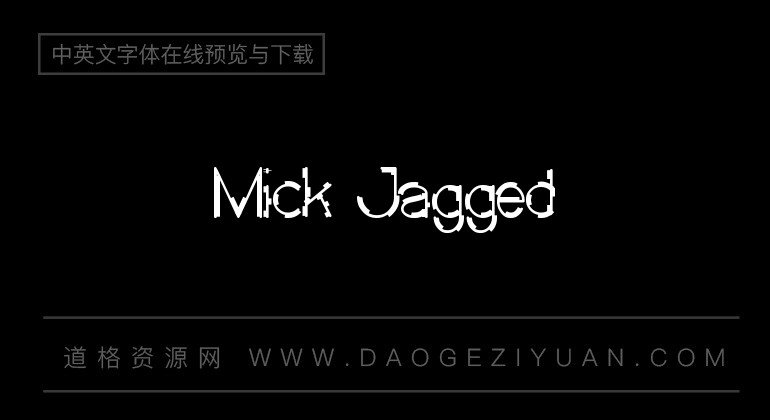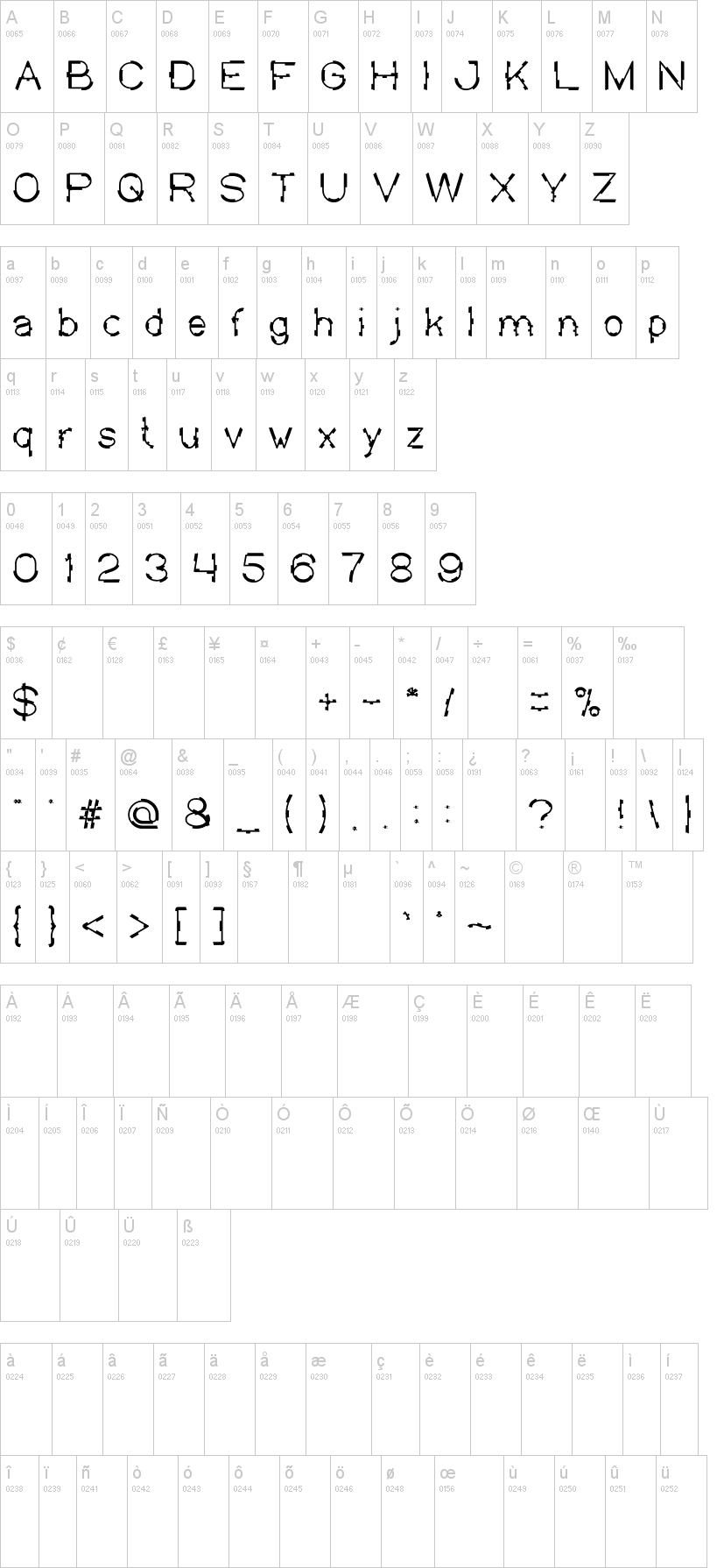
我想您可能指的是 Mick Jagger 字体,而不是 Mick Jagged 字体。 Mick Jagger 字体是一种手写风格的字体,以滚石乐队的主唱 Mick Jagger 命名,因为它的设计灵感来自于他的手写风格。 这种字体具有一种独特的,有点粗糙的感觉,看起来像是手写在纸上的字体,但实际上是计算机生成的。它的艺术风格适用于标题、标志和海报等设计项目。 Mick Jagger 字体由设计师 Ronnie Tjampitjinpa 和 Georgia Chapman 创造,可以从许多免费字体下载网站获得。内容介绍
Mick Jagged是一款非常不错的手写艺术字体,具有很好的视觉感,适合于文化类的宣传设计、商业类品牌的广告和产品包装设计以及个性化文字排版等较多场景。